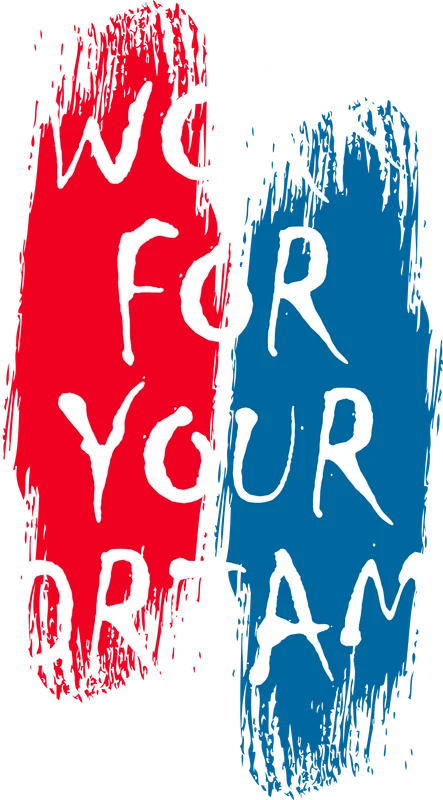
Động lực làm việc vì ước mơ, font chữ trắng
Động lực làm việc vì ước mơ, font chữ trắng — Truyền cảm hứng với thiết kế "Work for Your Dream" độc đáo. Phù hợp in trên áo thun, túi tote, sticker. Chất liệu in chuyển nhiệt sắc nét.
Trong hình có: slogan, vệt sơn
Phong cách: flat-design · Cảm giác: mạnh mẽ
Tông màu chủ đạo: đỏ, xanh dương